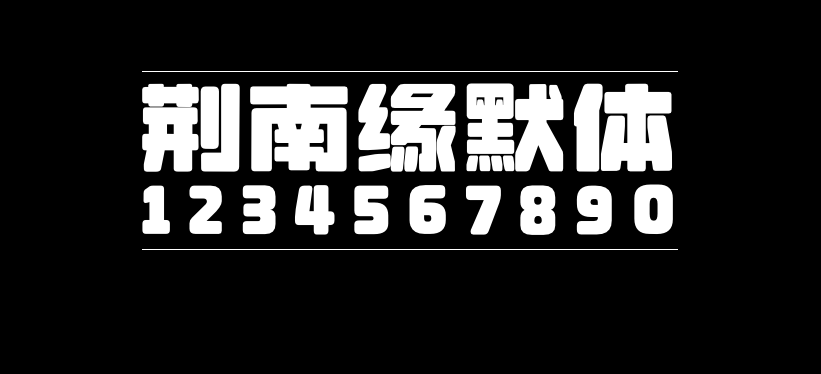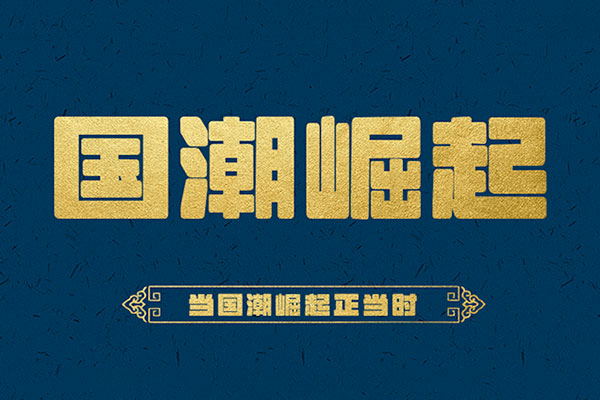
荆南缘默体
荆南缘默体(Kingnamtype Rounded Sinoheadline Regular)是中国大陆字体爱好者“皇帝的新冠”制作发布的一款中文字体。据作者介绍,一开始的字体风格还不想现在这样,圆角是后来逐渐加上去的,作者想要一种增加字体趣味性但是又不要看起来很像叠圆体之类的圆体美术体,于是就形成了如今的圆角。
荆南缘默体的理想设计用途:该字体非常适合店招、房地产广告、地铁公交站广告海报、线上及线下的各类产品宣传、个人VLOG封面标题字体等。
荆南缘默体包含BG2312规定的6763字,同时还包含了西文、数字、符号、日文平假名、日文片假名、注音符号、汉语拼音等,喜欢的赶快下载吧!
荆南缘默体字体效果预览